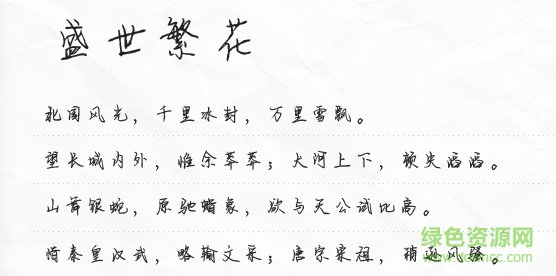
盛世繁花字體是一款獨(dú)具古風(fēng)運(yùn)維的藝術(shù)字體,字跡娟秀婉約,給你寧靜致遠(yuǎn)的觀賞體驗(yàn),讓文字變得更有內(nèi)涵,喜歡的朋友就來綠色資源網(wǎng)下載收藏吧!
執(zhí)年華為筆,寫盡一生風(fēng)月無邊;以江山為曲,歌盡一場盛世繁花。
本字體有文道字庫推出,以古風(fēng)為魂,以手寫體為魄,為大家?guī)順O為舒適的視覺體驗(yàn),可廣泛運(yùn)用于屏幕設(shè)計、詩歌編輯、海報印刷等場合。